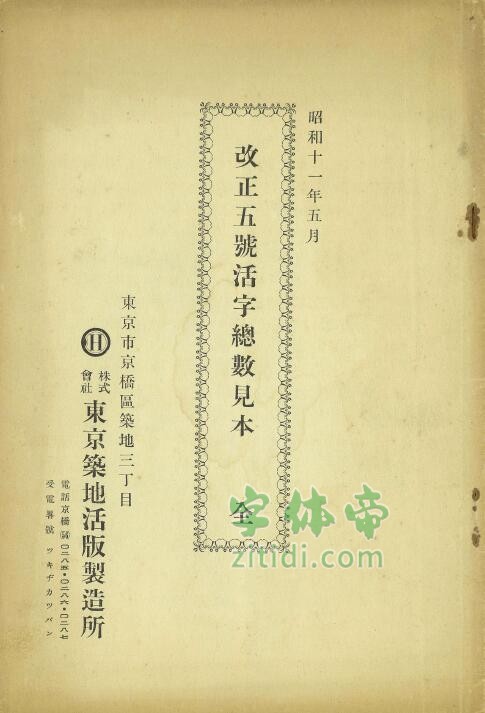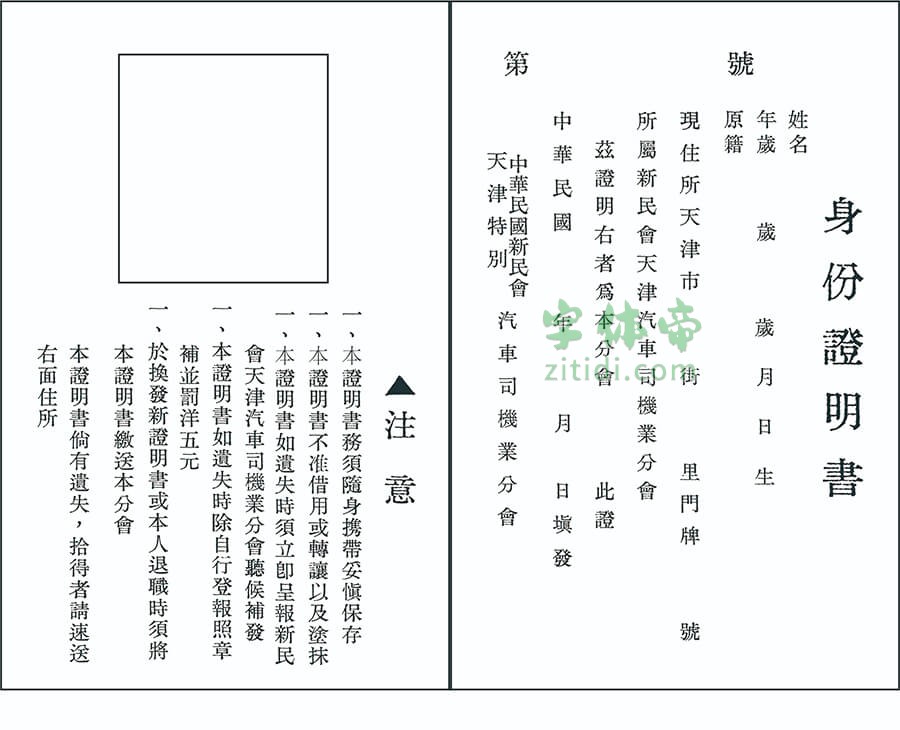
汇文筑地五号明朝体是百度“旧字形吧”吧主天王帝廷制作的一款可以免费商用的铅印风古籍复刻字体。据吧主描述,这款字体的诞生中间也经过了不少的曲折。
在很久之前吧主就一直有这样一个想法,做一个民国旧铅字的扫描字体,但却不知道怎么著手去做。主要困难是,要怎样才能一下收集齐几乎所有的汉字的字样?当然不可能买很多很多书籍报纸来一个个找一个个扣。那么有没有一本书能一次就包含了所有的汉字在内呢?答案是有的,那就是字典。
但是字典有另外一个问题。首先吧主的主要目的是做一个正文用的铅字字体,也就是一般常用的五号字体。而用字典很少用到这一字号大小,要不就是字头的大字,要不就是正文的小字。字头的大字扫描出来就会像著名的康熙字典体一样,比较适合作为标题字而非正文排版;正文的小字又太小,而且在这么多正文里扣出想要的字工作量会比只扣字头字大得多得多,不太现实。
那还有没有其他的书能方便地让我一下就取得尽可能多的、我想要的字号的字呢?这时吧主想到了一本重要的历史文献《简化汉字方案》。于是,在2018年12月,吧主在购买孔夫子旧书网了一系列的汉字改革方案的原始文件回来用于扫描。这些文件包括《汉字简化方案草案》、《拟定废除的400个异体字表草案》、《798个汉字简化表草案整》、《第一批异体字整理表》、《汉字简化方案》、《简化字总表》。甚至买了一本《第二次汉字简化方案草案》,几乎把所有相关文件拿到了手。
接着就是繁复的扫描、取字、整理分类、录入工作,然后经过一个春节假期,到2019年3月1日才完成了所有文字改革相关文件的收录。由于扫描的第一份文件是《文汇报》上面的《汉字简化方案草案》,又取“收集汇集各方来源的字模来制作成字体”的含义,吧主决定将这一字体命名为《汇文明朝体》。
但是,即使这样做下来,收录的字也仅有4000多字,其中缺了很多没有经过简化的传承字。这个程度还没办法正常使用。怎么将剩下的传承字收录进来又成了头痛的问题。这个时候,在外网闲逛的时候发现了这样一个宝藏,那就是《改正五号活字总数见本 全》这本古籍。这本小册子是日本昭和11年(1936年)东京筑地活版製造所出版的,其字形是现在日本明朝体之源流,和当时中国的铅字字形一样源自于康熙字典的字形。
这本小册子收字丰富,非常适合用来补充字库。于是从3月3日吧主就开始著手整理制作筑地五号字体。筑地五号据作者所述,是收录汉字总数八千八百七十八种,但经过吧主的整理,这个数字并不对头,不管怎么数都只有8658个字。其中还有117个unicode没有收录的字,和26个重复的字。所以共收录8515个字。然后吧主又顺便收录了所有平假名片假名和241个万叶假名跟变体假名。然后补了西文字母还有一些图形符号。所以汇文筑地五号明朝体整个字体收录9262个字符。
吧主本来是计划用《汇文筑地五号明朝体》和他之前制作的《汇文明朝体》合并成一款字体,但是发现这两款字形风格不太一致!合并后很明显看得出来是两种字!这就很难受了。所以吧主现在放弃了这个计划,而是另外想办法把《汇文明朝体》的简繁文字补全。现在吧主也一直在对汇文明朝体进行补全工作,这是一个漫长而艰苦的过程,相信在不久的将来汇文明朝体就会跟大家见面,让我们一起期待这款字体的面世吧!
现在这款汇文筑地五号明朝体算是在制作《汇文明朝体》的过程中衍生副产品,吧主还是无私地放出来免费给大家使用。因为这款字体因为是属于番外性质的字体,所以古籍中有的字就收录,没有的字也不会进行补充。而吧主正在全力制作《汇文明朝体》,而汇文明朝体则会以尽量不缺字为原则进行制作,也就是会包括常用的简体和繁体字,十分令人期待!!